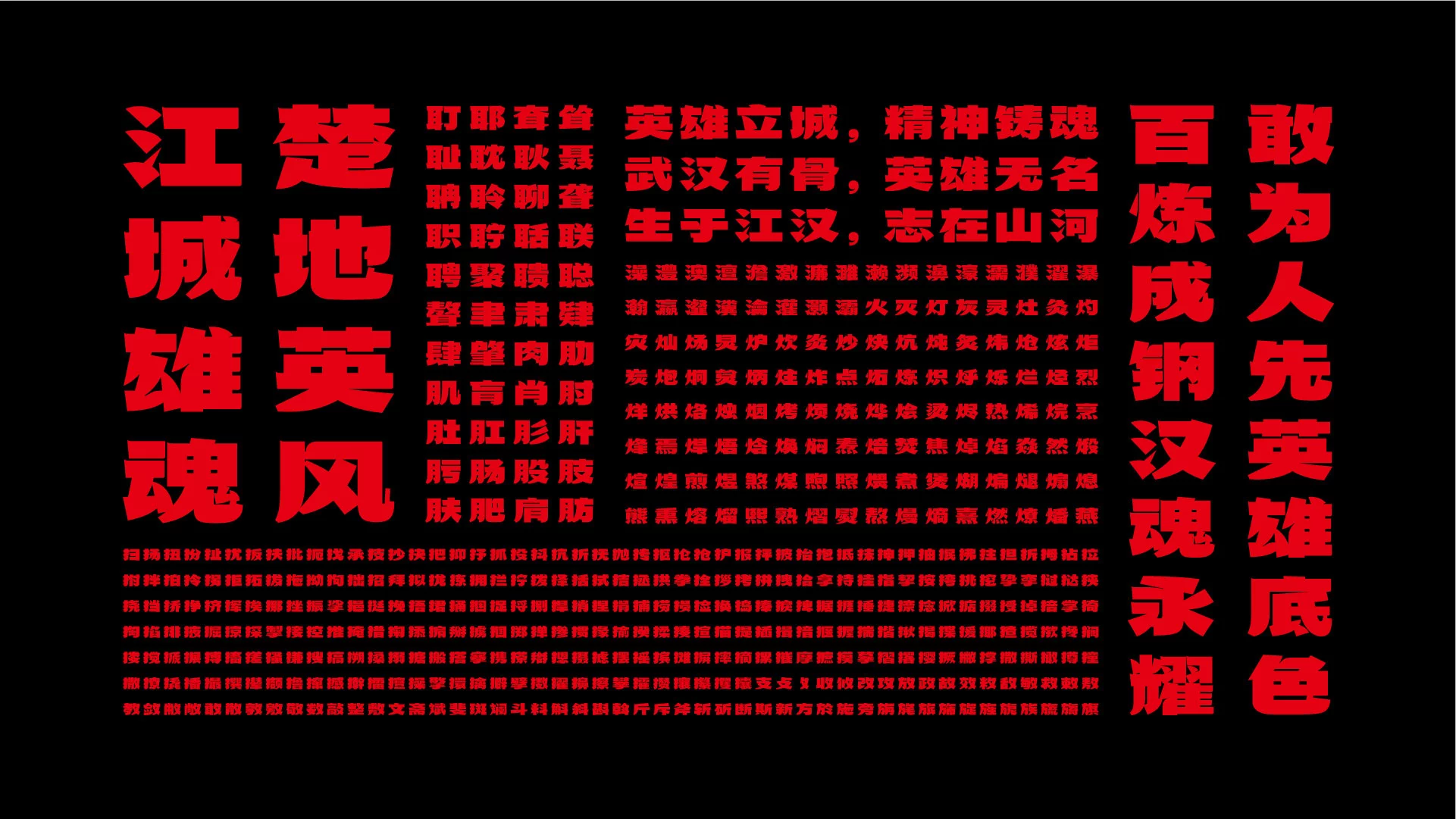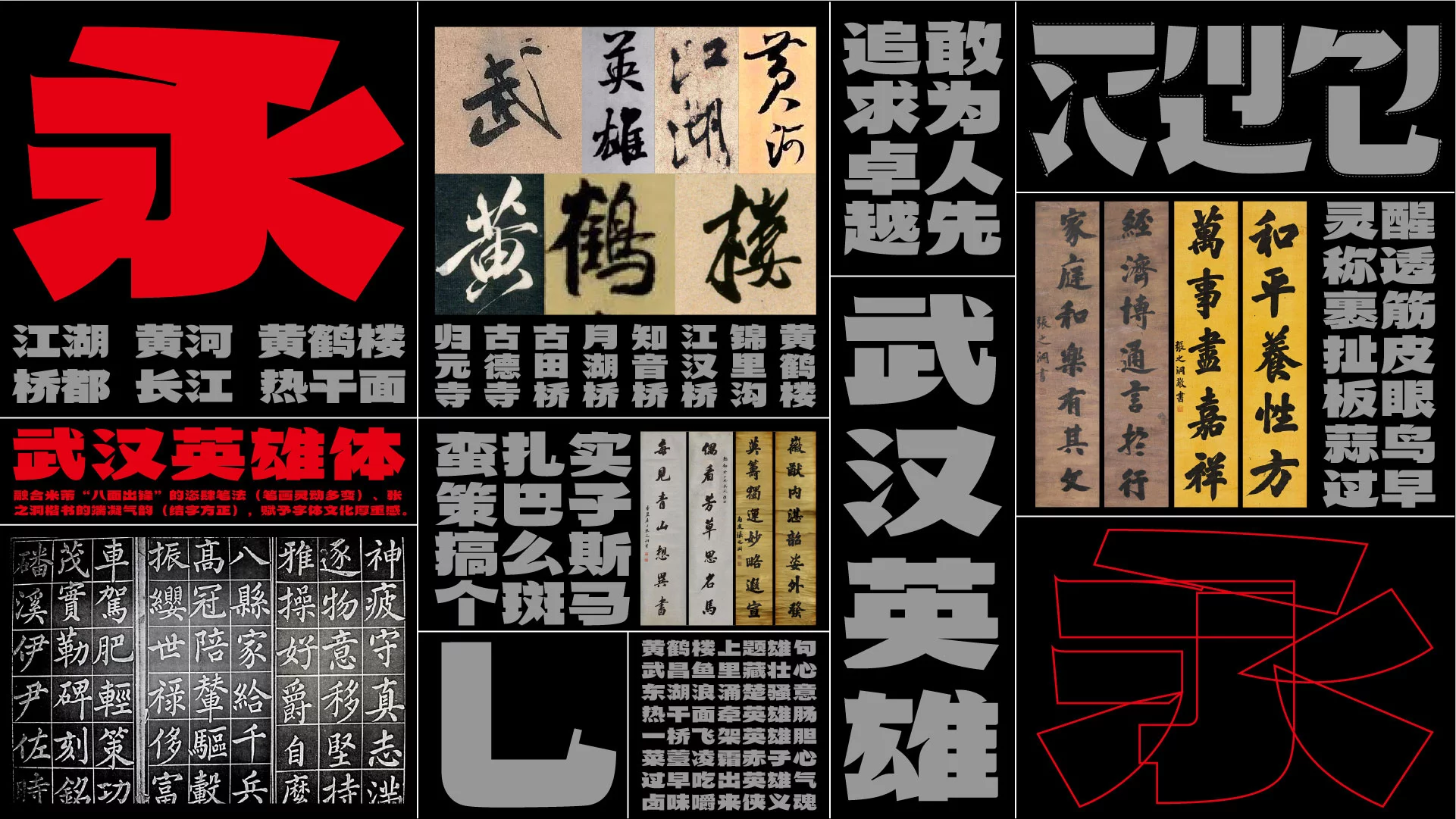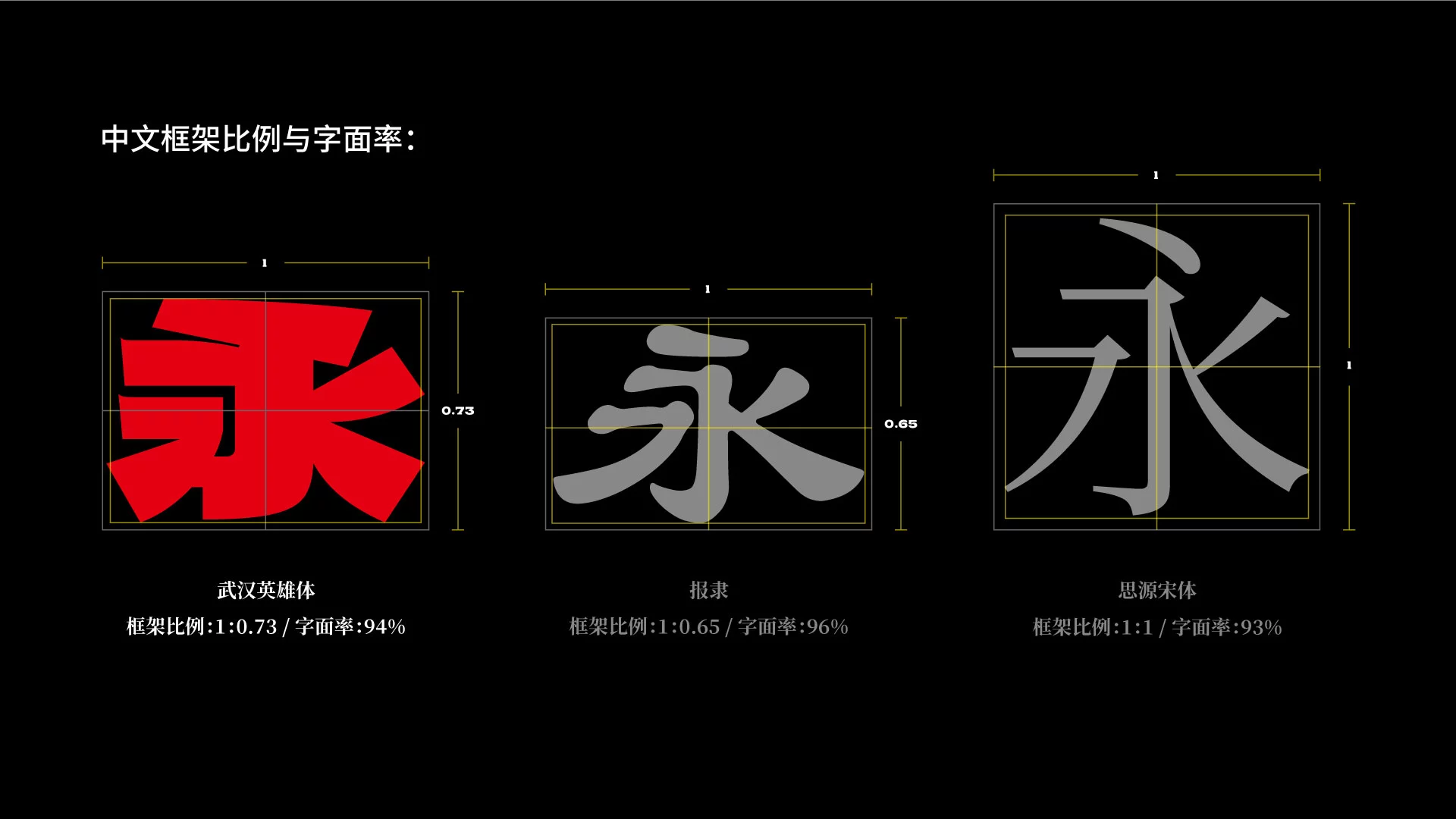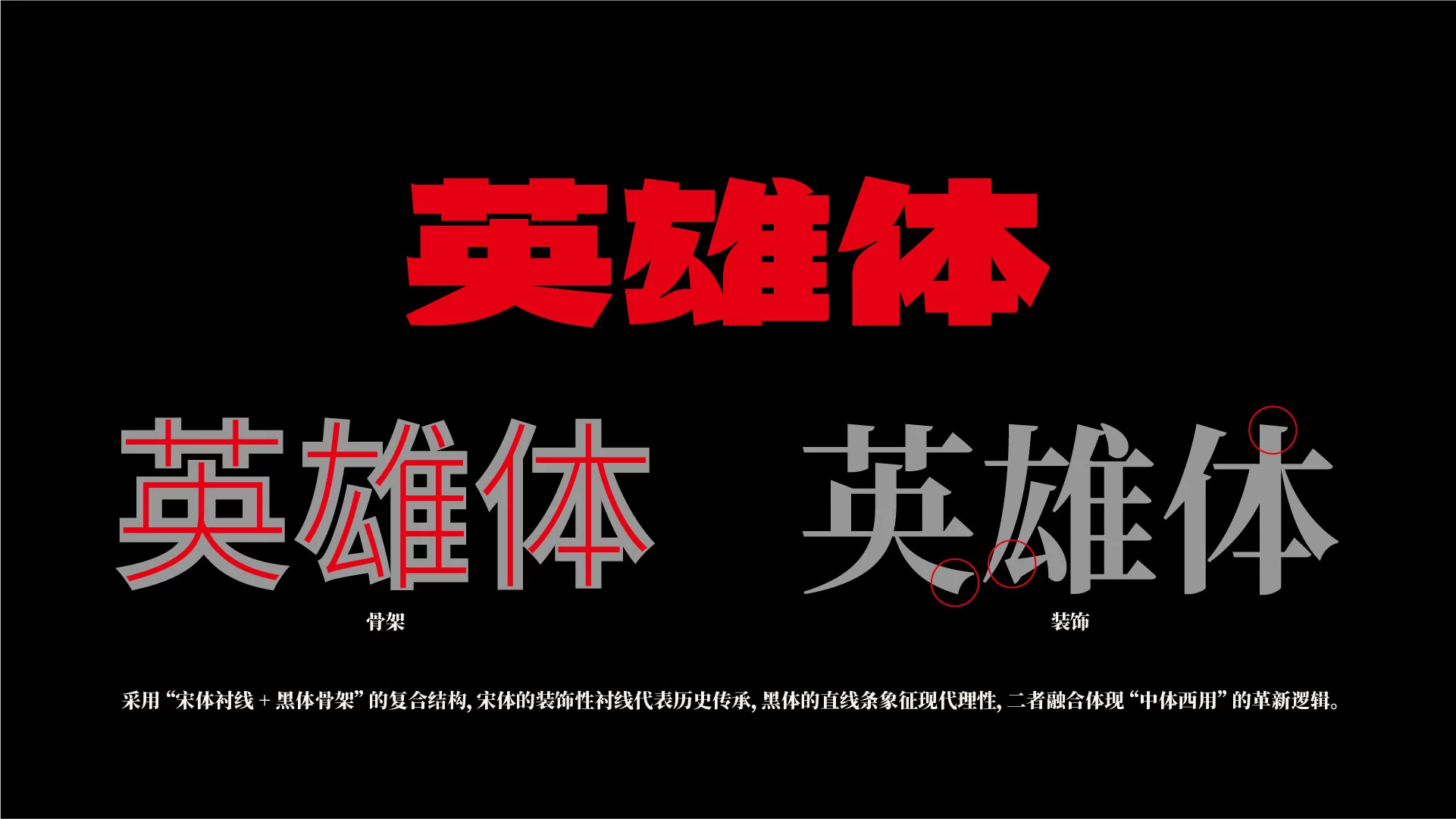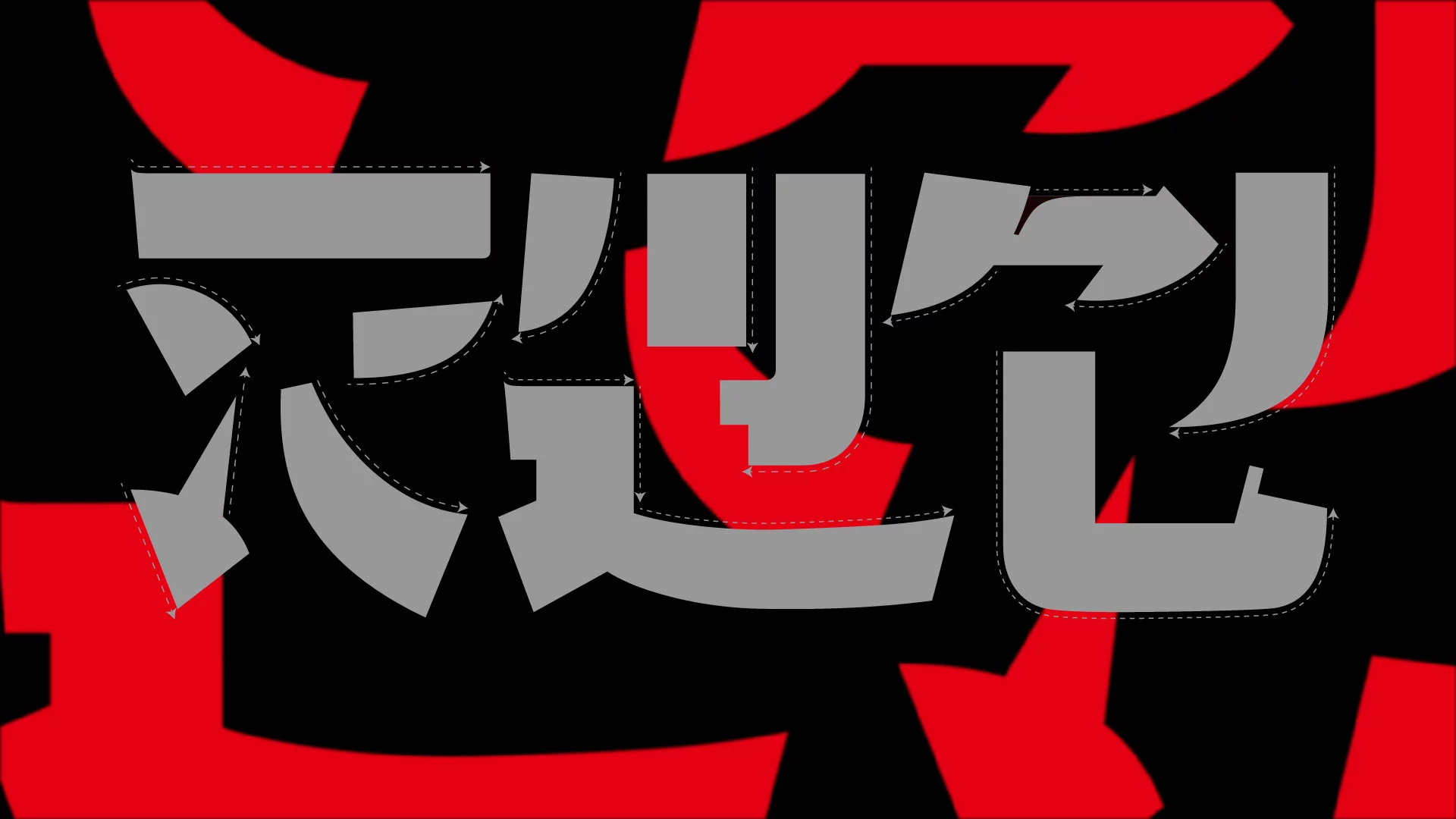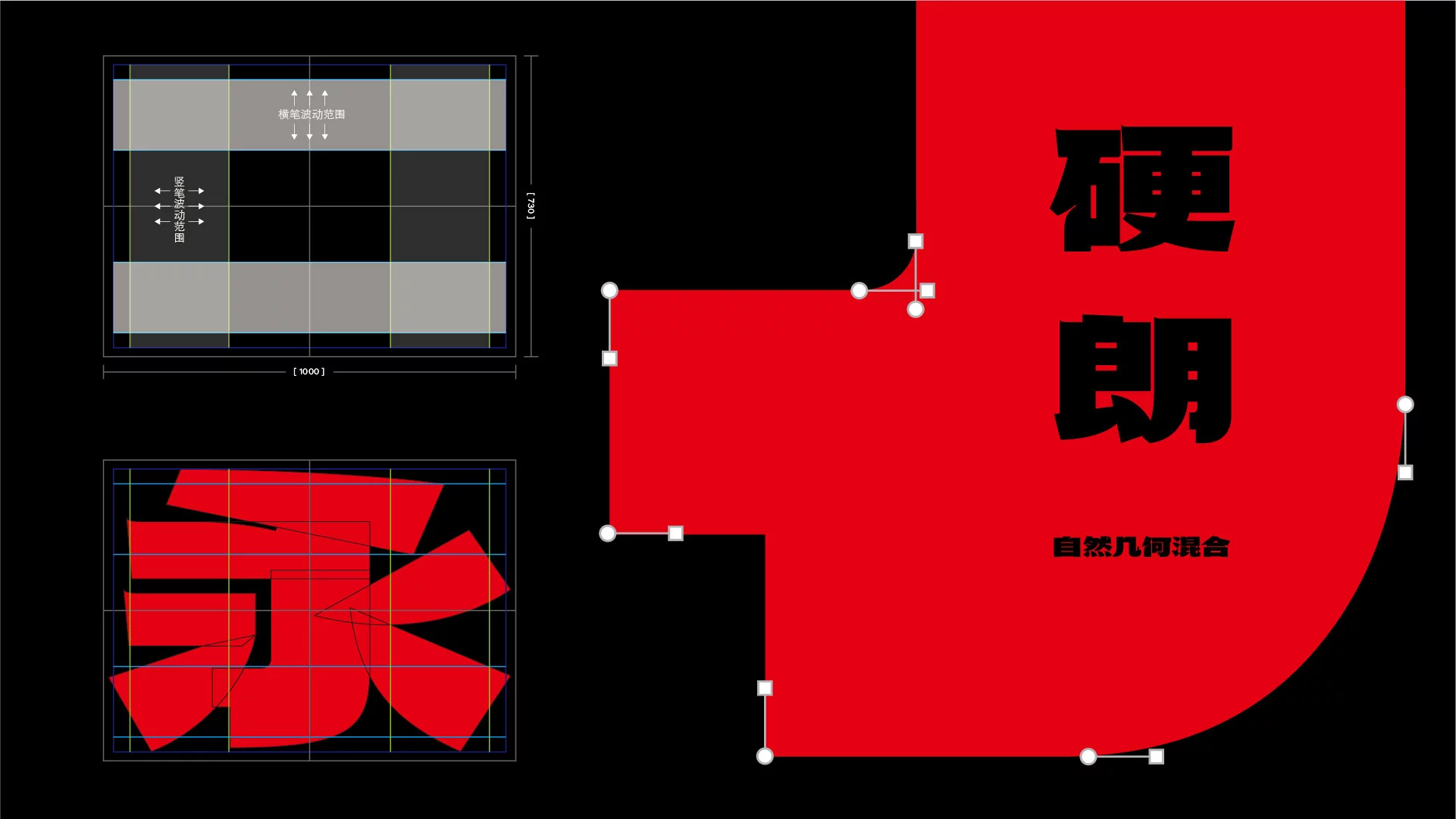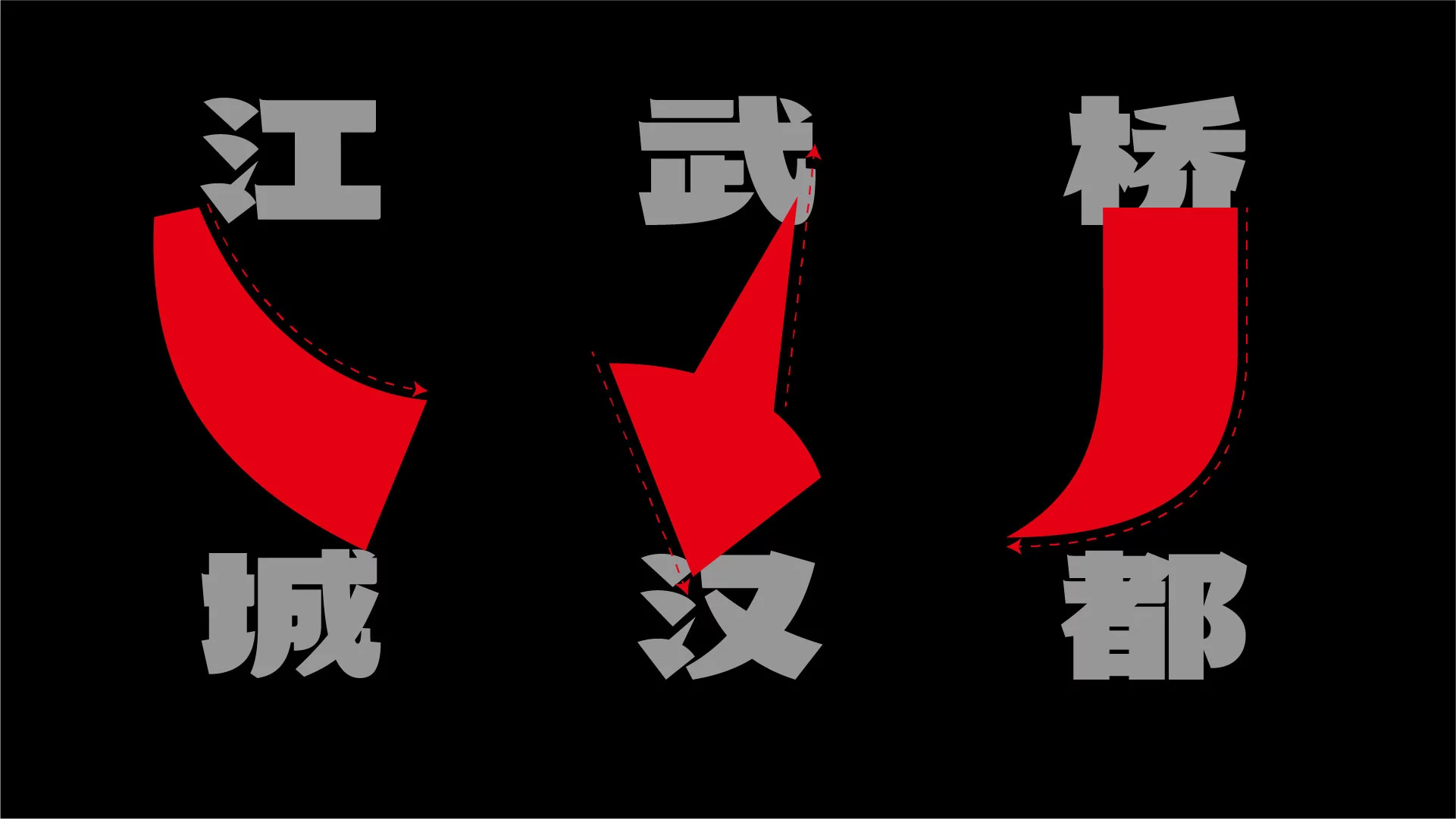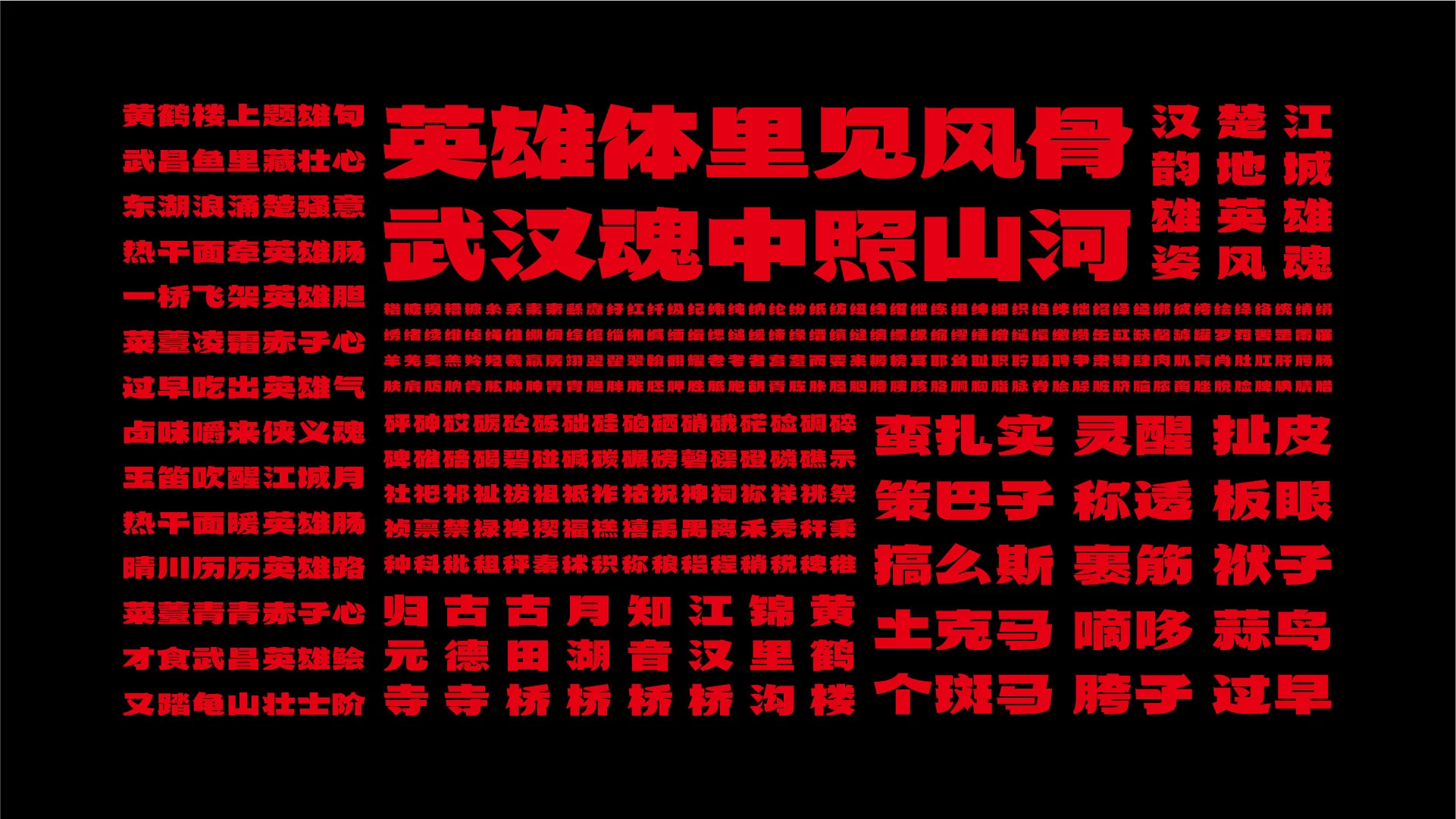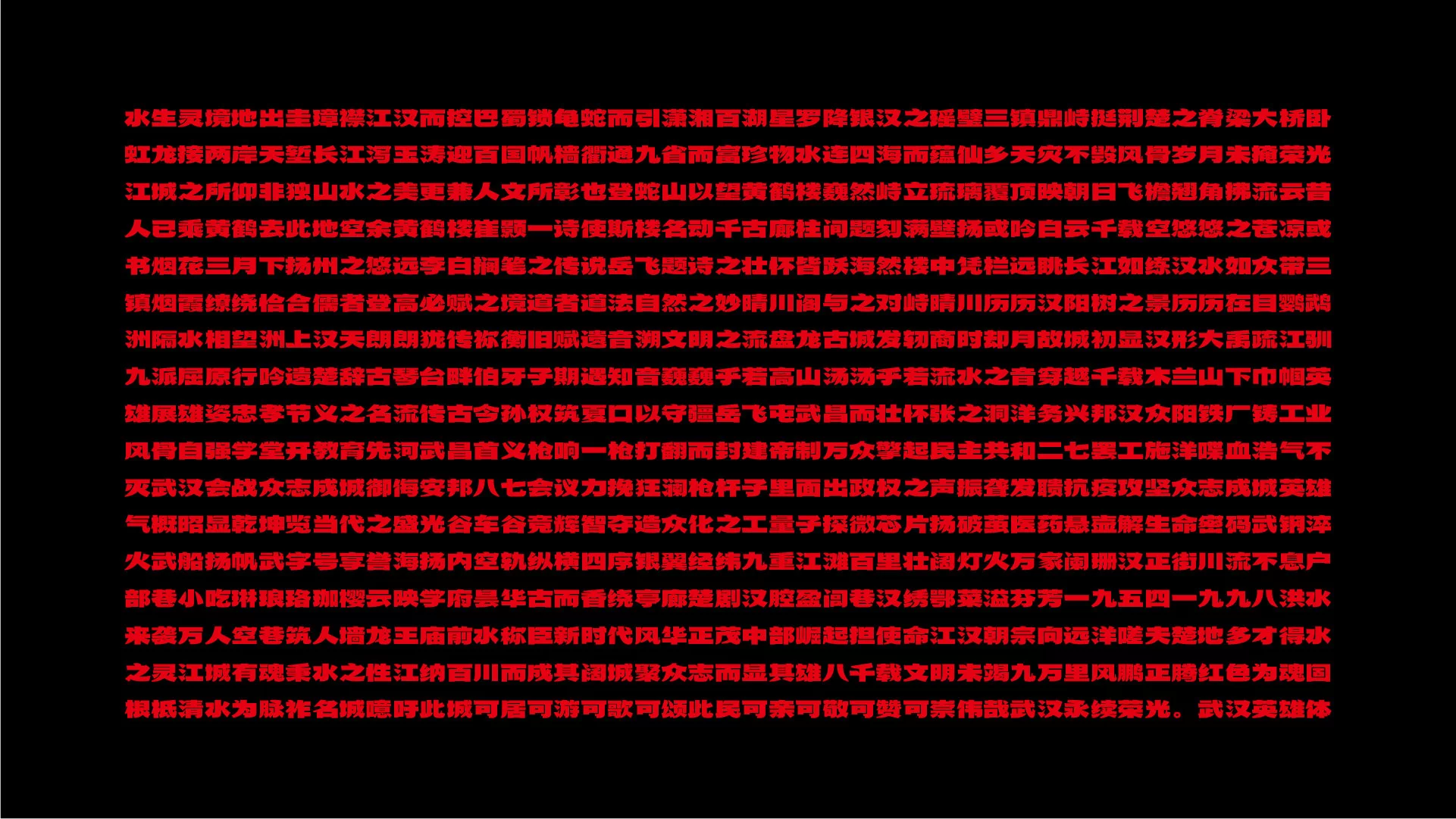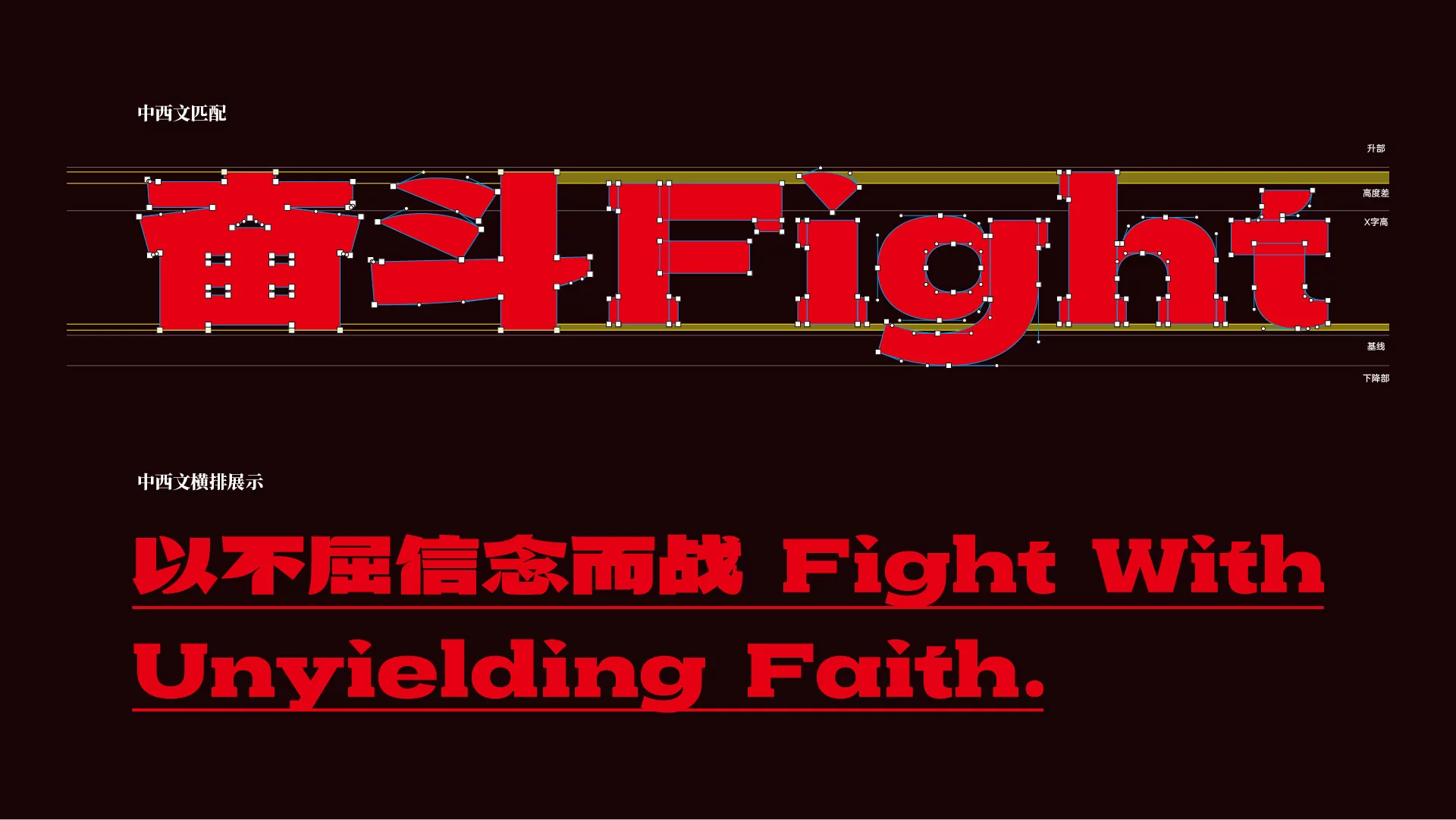
武汉英雄体
当一款字体开始讲述一座城市,它便不再只是文字的载体。
武汉英雄体正是这样一款充满城市印记的原创中文美术字体。它由武汉工商学院徐郑冰教授团队设计开发,共收录6700余个汉字,并正式向社会免费开放商业使用。字体以武汉深厚的历史文化为创作基础,在现代字体设计中融入荆楚文化、城市建筑和地方人文,让每一个汉字都拥有属于武汉的独特气质。
相比传统黑体强调理性、宋体强调阅读,武汉英雄体更加注重文化表达。它没有刻意追求复杂的装饰,而是在字形结构、笔画变化和整体节奏中寻找平衡,让字体既保持现代设计所需要的清晰度,也能够传递武汉这座城市豪迈、大气、坚韧的精神面貌。因此,无论作为文旅宣传还是品牌视觉,它都拥有很高的辨识度。
很多城市都有自己的建筑地标,也有属于自己的文化符号,但真正能够代表一座城市气质的字体却并不多见。在设计团队看来,字体不仅承担着信息传递的作用,同样也是一种文化表达方式。相比静态的城市Logo或宣传海报,一套字体能够持续出现在城市宣传、文化活动、公共空间以及各种设计作品中,更容易成为一座城市长期传播的视觉语言。
也正因为如此,武汉英雄体从一开始就没有定位成普通的美术字体,而是希望通过文字,把武汉的历史底蕴、人文精神以及城市记忆重新呈现出来。当人们阅读这些文字时,不只是看到字体本身,也能够感受到属于武汉的文化温度。
为了让字体真正具有武汉特色,设计团队并没有闭门造车,而是花费大量时间走进城市寻找灵感。
从黄鹤楼到武汉长江大桥,从江汉关到起义门,再到汉正街、兰陵菜市场,一处处熟悉的城市地标、一块块历经岁月的老招牌,都成为设计团队研究的对象。他们希望通过这些真实存在的城市景观,找到最能代表武汉气质的视觉元素,而不是简单地添加一些装饰图案。
除了城市建筑,团队还查阅了大量荆楚铭文、本土碑刻以及传统书法资料,从历史文字中寻找属于武汉的文化基因。经过不断整理和提炼,这些来自城市不同角落的元素,最终都被融入到字体设计之中,成为武汉英雄体最鲜明的特色。
从整体结构来看,武汉英雄体融合了黑体、宋体以及北魏碑刻的部分设计特点,在现代字体结构中加入传统书法的笔意,使字体既具有力量感,也保留了丰富的文化韵味。
在框架设定上,没有沿用常规字库1:1的正方形框架。而是从传统书法中汲取灵感,将字面设定得略微宽扁,中宫紧紧收窄,整个字体的重心向下沉,这使得字体更显稳重。
字体没有采用传统中文字体较为方正的比例,而是适当拉宽字面,使整体更加宽博舒展,中宫略收、重心偏低,形成稳重厚实的视觉效果。这种比例不仅让字体更符合现代横版排版,也让大字号标题拥有更强的视觉冲击力。
笔画处理同样体现出鲜明的设计特色。横画平稳有力,竖画挺拔厚重,转折干净利落,而撇、捺、钩等笔画则保留了自然舒展的书写节奏。为了适应现代数字媒体显示,部分笔画还进行了切角和圆角优化,使字体在不同尺寸下都能够保持清晰稳定的阅读效果。
在西文的适配里,采用了粗衬线的设计。在西文衬线字体里,这种风格有种独特的历史感、力量感,这和英雄体的气质也是很吻合的,算是很经典的搭配了。
武汉英雄体最有意思的地方,并不是简单地使用武汉元素,而是把这些元素真正融入到了字体结构之中。
例如字体中舒展向上的捺画,灵感便来自黄鹤楼飞檐的建筑轮廓。设计团队没有直接复制飞檐造型,而是提取其轻盈舒展的线条,让字体在收笔时拥有更加自然的延伸感,也让整个字形显得更加富有生命力。
而"武"字中极具力量感的戈钩,则参考了武汉历史中的英雄文化,希望通过更加开阔有力的笔画表现出城市坚韧、果敢的精神气质。部分竖画采用上窄下宽的处理方式,则借鉴了武汉长江大桥桥墩稳固厚重的结构特点,让字体整体拥有更加扎实的视觉重心。
这些设计细节或许不会第一时间被发现,但正是这些隐藏在笔画中的文化语言,让武汉英雄体拥有了区别于普通标题字体的独特魅力。
设计一套完整的中文字体,从来都不是一件轻松的事情。在这套字库里,一共包含了6700多个汉字。没有AI的一键生成,没有套用现成的模板。这里面每一个字,都是团队成员在电脑前,用鼠标一笔一划纯手工设计出来的。
据徐郑冰教授回忆,每个人每天撑死了也就只能完成10个字左右。整个团队足足耗时两年,才把这套字库打磨成型。
单单是字体基础框架,就推翻重来了12版。
武汉英雄体是一款典型的展示型中文字体,非常适合作为标题使用。在文旅宣传、城市品牌、文化展览、博物馆视觉、地方IP以及文创产品设计中,它能够快速建立地域文化氛围,让作品更具辨识度。如果用于武汉相关主题,更能够强化城市特色,提升整体视觉感染力。
除此之外,武汉英雄体同样适用于影视片头、纪录片字幕、短视频封面、品牌海报、企业文化宣传以及大型活动主视觉等设计场景。宽博稳重的字形比例能够很好地适配现代数字媒体,在LED屏幕、商业海报以及视频画面中都具有良好的表现力。
武汉英雄体不仅是一套免费商用中文字体,更是一套承载武汉城市文化与荆楚精神的原创字体作品。设计团队将黄鹤楼、长江大桥、地方碑刻以及传统书法等文化元素融入字形设计,让每一个汉字都拥有鲜明的地域特色与文化底蕴。